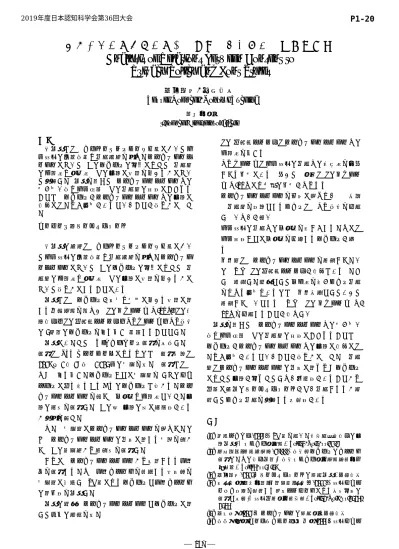
プライバシーポリシーへの同意とフォントの関係性分析
Analysis of Relations between Consent to
Privacy Policy and Font Styles
概要
本分析では、インターネットサービス等において個 人情報の収集方法や利用目的を定めたプライバシーポ リシーについて、そのフォントの変化によって、利用者 の信頼感や安心感などの印象に影響を与えるかについ て検討した。分析を通じて、プライバシーポリシーへの 向き合い方や個人意識などの利用者の属性にこだわる ことで、フォントがプライバシーポリシーへの印象に 有効にはたらく場合があるということが明らかになっ た。 キーワード:パーソナルデータ 本分析の目的は、インターネットサービス等におい て個人情報の収集方法や利用目的を定めたプライバシ ーポリシーについて、そのフォントの変化によって、利 用者の信頼感や安心感などの印象に影響を与えるかに ついて明らかにすることにある。 分析では、フォントが広告や商品に与える影響に関 する先行研究を踏まえ、HG 丸ゴシック M-PRO・HG 教 科書体・HG 創英角ポップ体・MS ゴシック・MS 明朝 の5種類のフォントを取り上げ、比較することとした。 分析にあたって、Web アンケート調査を実施した。 調査は NTT コムリサーチによるもので、調査期間は 2019 年 1 月 18 日、1,105 人の回答を得た。調査では、 まず、取り上げたフォントごとに回答者を5 つのセグ メントに割り振りそれぞれのフォントで書かれたプラ イバシーポリシーを見せ、不安感や信頼感といった印 象の程度を調査した。その後、印象の差に独立性がある か検定を行った。 また、回答者にプライバシーポリシーを読ませたの ち、プライバシーポリシーの内容に関する問題を解か せ、その正答率から理解度を調査した。 さらに、プライバシーポリシーから想起される企業 像を調査するため、企業イメージを表現する形容詞を 回答者に提示し、SD 法によりフォントと企業イメージ の関係性を分析した。 分析の結果、プライバシーポリシーとフォントに関 して以下の知見を得た。 HG 創英角ポップ体はプライバシーポリシーへの 信頼感を下げる。 MS ゴシックは個人情報の利用への抵抗感を増加 させる傾向にある。加えて、女性はHG 丸ゴシッ クM-PRO にも同様の傾向がみられる。 プライバシーポリシーを入念に読むような、慎重 な利用者を対象とするサイトは、MS 明朝を使用 しないほうが良い。 個人情報の利用への不安感を小さくするためには、 個人属性ごとに不安感を低減するフォントが異な る。 事業者は、プライバシーポリシーを理解させたい のならば、HG 創英角ポップ体が有効である。ただ し、理解した結果として不信感を抱きサイト利用 をやめる場合もあるので、事業戦略としてあえて 理解させないとするならば、HG 丸ゴシック M-PRO を使用することが望ましい。 分析を通じて、プライバシーポリシーへの向き合い 方や個人意識などの利用者の属性にこだわることで、 フォントがプライバシーポリシーへの印象に有効には たらく場合があるということが明らかになった。利用 者はプライバシーポリシーの内容に関わらずフォント によって印象が変わってしまう可能性があることから、 冷静に自分のパーソナルデータがどう利用されるか確 認してサイト利用を検討する必要性がある。文献